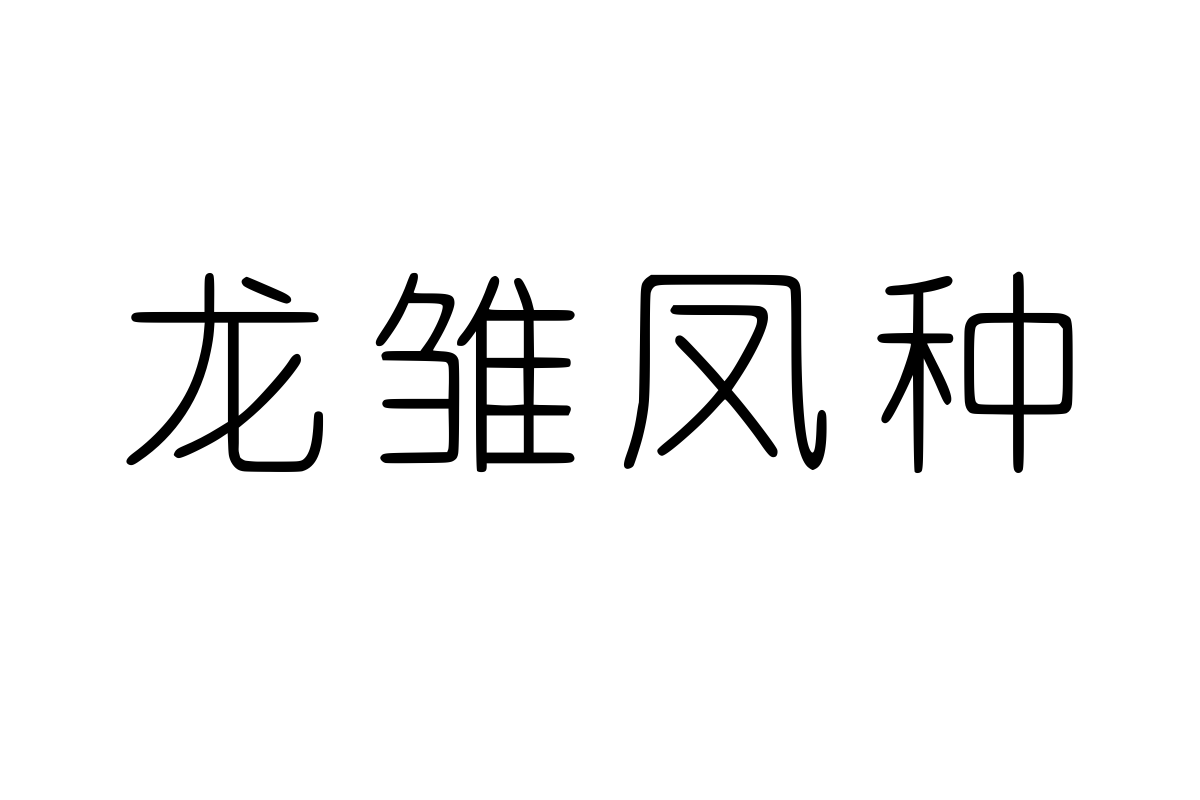
兰米细圆字体是一款由北京华文时代科技股份有限公司设计开发的中文字体,具有独特的设计风格和特点。
该字体采用了圆润的字形设计,线条流畅自然,给人一种柔和、亲切的感觉。字体结构紧凑,笔画粗细均匀,易于阅读和书写。同时,兰米细圆字体还注重细节的处理,如字形的起伏、字距的调整等,使得整体效果更加和谐统一。